השאלון עם עדן מייזלס
הכירו את עדן מייזלס, ילידת 1998, בוגרת תואר ראשון בתקשורת חזותית בביה״ס לעיצוב של אוניברסיטת חיפה (או כפי שהאולד־סקול עוד מכנים – ויצו). חיפאית מאז ומתמיד, חיה כיום באזור הכרמל עם בעלה לעתיד וכלבלב מתוק שהצטרף אליהם לא מזמן. עדן מחוברת במיוחד למיתוג ולעיצוב גרפי קלאסי, למוצרי פרינט ולטיפוגרפיה – אך יש לה גם פינה חמה בלב לעולמות ה־UX/UI. היא רואה בעיצוב כלי שמסוגל להעביר מסרים ורגשות בלי הרבה מילים – “פשוט דרך תחושות ואסתטיקה ייחודית,” כלשונה. כשאינה מעצבת, סביר שתמצאו אותה מבשלת במטבח או סועדת במסעדות טובות, מבלה בים, מאזינה למוזיקה לטינית או ישראלית נוסטלגית, או על הספה מול תוכניות בישול, סדרות תקופתיות וטראש טלוויזיוני.
על איזה פרויקט מעניין עבדת לאחרונה?
אין ספק שהפרויקט הכי מורכב ומעמיק שיצא לי לעבוד עליו לאחרונה הוא פרויקט הגמר שלי. הפרויקט מכונה ׳אסתריקה׳ על שם סבתי ז״ל, ילידת סלוניקי וצאצאית למגורשי ספרד דוברי לאדינו. מדובר בעבודה טיפוגרפית שעוסקת בביטוי החזותי של שפה שהכרתי כמדוברת בלבד כל חיי, במטרה להנכיח פרק היסטורי שנזנח ולשמרו, עיצבתי פונט לכתב הסוליטריאו – כתב־יד יהודי־ספרדי ששימש את דוברי הלאדינו, בין היתר במדינות הבלקן, לכתיבה יומיומית. הפרויקט הוא בעל חשיבות היסטורית תרבותית ולאומית והערך שלו עצום בעיניי, וכולי תקווה שהוא יוכל להוות מצע עדכני לפיסת היסטוריה שמקבלת חיים חדשים.
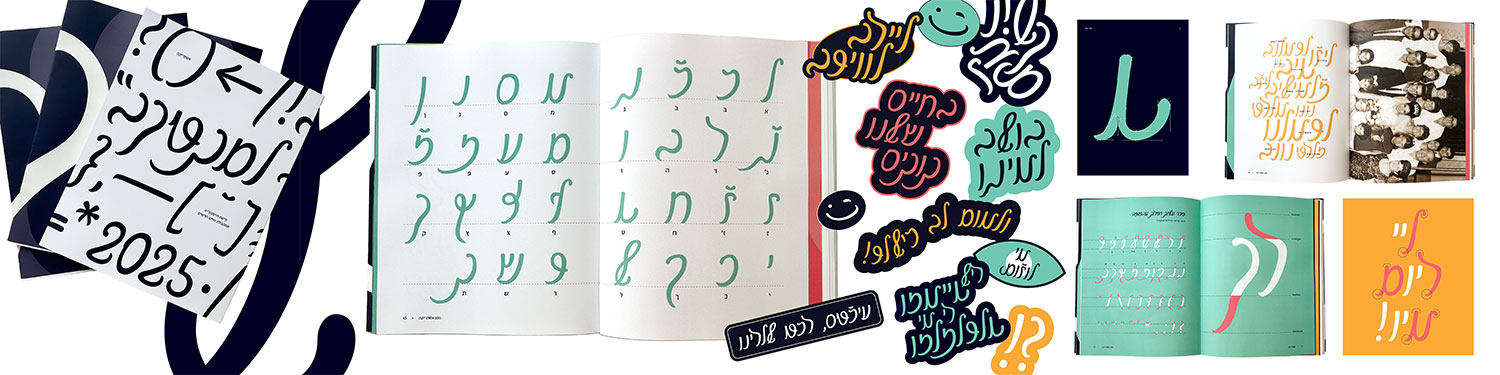
הפרויקט ״אסתריקה״ של עדן נולד מתוך חיבור עמוק לשורשיה המשפחתיים ולמורשת התרבותית שלה. ההשראה הגיעה מסבתה ז״ל, ילידת סלוניקי וצאצאית למגורשי ספרד דוברי לאדינו. דרך סיפורי ילדות, ביטויים משפחתיים ושפה שמילאה את הבית, נוצרה נקודת מוצא למחקר תרבותי־טיפוגרפי. עדן מספרת: ״לשפת הלאדינו נחשפתי מילדות, כאשר מילים וביטויים שלה חלחלו ללקסיקון המשפחתי שלי – ׳שריקה לה לוקה׳, ׳פוסטמה׳, ׳טרונשו׳, ואפילו הביטוי ׳שנת תרפפ״ו׳ – מוכר לכם? כולם מלאדינו.״ השפה, שנכתבה בעבר בכתב־יד יהודי־ספרדי בשם ״סוליטריאו״, כמעט ונעלמה עם החייאת העברית. בפרויקט הגמר שלה בחרה עדן להחיות את הכתב באמצעות עיצוב גופן חדש, המבוסס על מחקר אותיות מתוך מסמכים עתיקים. מטרת הפרויקט היא ״להנכיח פרק היסטורי שנזנח, לפעול למען שימורו, ולהעניק לו חיים מחודשים בעולם העיצוב העכשווי.״ ניתן לקרוא עוד על הפרויקט כאן.
מה את עושה כשאין לך מוזה?
לפעמים צריך להתרחק בשביל להתקרב. לפעמים הניתוק מהמחשבה על מה צריך לעשות או איך משהו צריך להיראות הוא שמאפשר לי לחזור ולחשוב עליו מכיוון אחר. לא פעם הייתי צריכה להניח לדברים בצד לתקופה של יום-יומיים ואפילו שבוע רק כדי להבין מה הכיוון שנכון ללכת איתו. שמתי לב שדווקא בלילות, כשמחשבות לא עוזבות אותי ואפילו נכנסות לי לחלומות, פתאום, משום מקום, עולה רעיון ואני ישר קמה וכותבת אותו לעצמי בפתקים שלא אשכח. כשמדובר בפרויקטים רחבים, הרשימה של הרעיונות מתארכת. כל דבר אפילו הכי שטותי אני מוסיפה לרשימה, אפילו אם זה משהו שאני בכלל לא רוצה לעשות, או שהוא רק בגדר אופציה, או שמישהו אחר אמר לי אותו מתישהו (וכמובן שמלא רעיונות נופלים בעריכה). חוץ מזה, אפשר למצוא כל כך הרבה מקורות השראה אצל מעצבים אחרים וברשת, אבל חשוב מאוד לא לטבוע בתוך זה ולא להיכנע לקלישאות עיצוביות או לטרנדים חולפים. זה האתגר הכי גדול לדעתי.
מה את עושה בשביל הכיף?
אני ממש, אבל ממש, אוהבת אוכל ובישול, וממש כיף איתי במסעדות, אני נשבעת, אפילו שאני צמחונית (או ליתר דיוק, פסקטריאנית, שזה צמחונית אבל אוכלת דגים). פעם אפילו כתבתי סיפור קצר על כמה אני גרגרנית שמתלהבת משילובים מוזרים ומתמוגגת מחלמון ביצה שנשפך. חוץ מזה, אני מאוד אוהבת את הים ולטייל בטבע. באותה נשימה, אני גם אוהבת להיות בטטת כורסא ולראות תוכניות טראש בטלוויזיה, או תוכניות בישול וסדרות תקופתיות עם נופים ותפאורה מטורפת, טירות וויקינגים שרמנטיים.
יש לך הרגל מגונה?
בטוח שיש לי. לכל אחד יש. אני צריכה רגע לאתר אותו ולהחליט אם יש לי מספיק אומץ לומר אותו ככה בפומבי... אם באוכל עסקינן, אז אולי ההרגל המגונה שלי הוא שאני מרבה לאכול ברעש לפעמים (סורי למי שזה מפריע לו תמיד, זה לא בכוונה), ואני אפילו רוקדת לי תוך כדי האכילה אם ממש טעים לי. תקראו לזה ביטוי לתאווה הבלתי מוסברת שלי לאוכל. נ.ב. אני עדיין משחקת קנדי קראש לפעמים, מטפחת את הרזומה שלי שם עוד מכיתה ט׳.